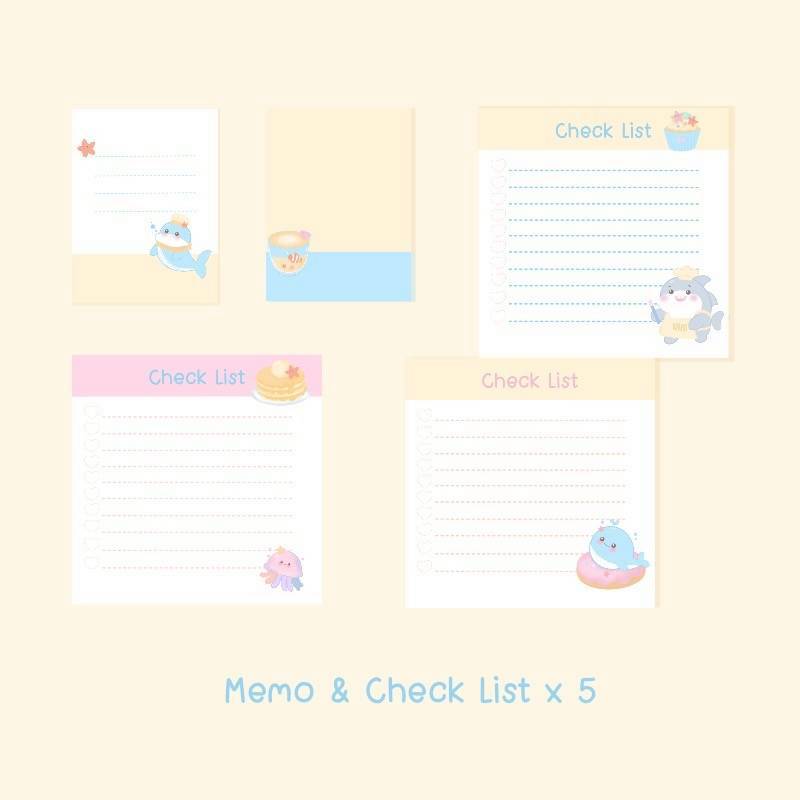
Font CkPluto
ชื่อสินค้า : Font CkPluto 💙
🔸 ฟอนต์ลายมือแนวน่ารักอวบอ้วน เน้นความเป็นระเบียบเรียบร้อย ทำให้ดูอ่านง่ายสบายตา ดูไม่น่าเบื่อ และยังมีไฟล์อิโมจิน่ารักๆ ที่ใช้แทนเลขไทยให้ด้วยค่ะ 🥰💙
🔹 A cute and chubby handwritten font that emphasizes neatness and order, making it easy to read and not boring. There is also a file of cute emojis that can be used instead of Thai numbers. 🥰💙